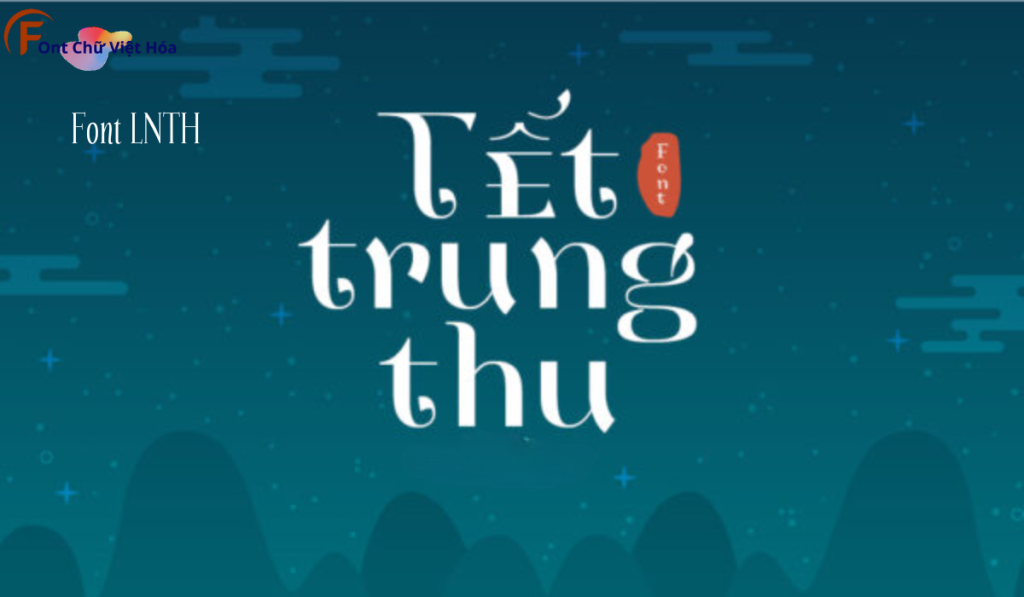
Font LNTH Henri Modeste Việt Hóa
Tác giả: LNTH
Bộ Font: LNTH
Kiểu chữ: Chữ có chân
Font LNTH Henri Modeste Việt Hóa là một font chữ thanh lịch, thuộc bộ LNTH, với thiết kế tinh tế và cổ điển. Phong cách của font này phù hợp với các dự án thiết kế cần sự trang nhã và sang trọng, như thiệp mời, bìa sách, hoặc logo. Font LNTH Henri Modeste Việt Hóa mang đến sự thanh lịch và dễ nhận diện, ứng dụng trong các lĩnh vực sáng tạo. Đặc điểm hình dạng của font bao gồm các đường nét mềm mại và tinh tế, giúp tăng tính thẩm mỹ và sự chú ý. Việc Việt hóa font giúp người dùng dễ dàng sử dụng trong các thiết kế tiếng Việt, mang lại sự tiện lợi và linh hoạt.